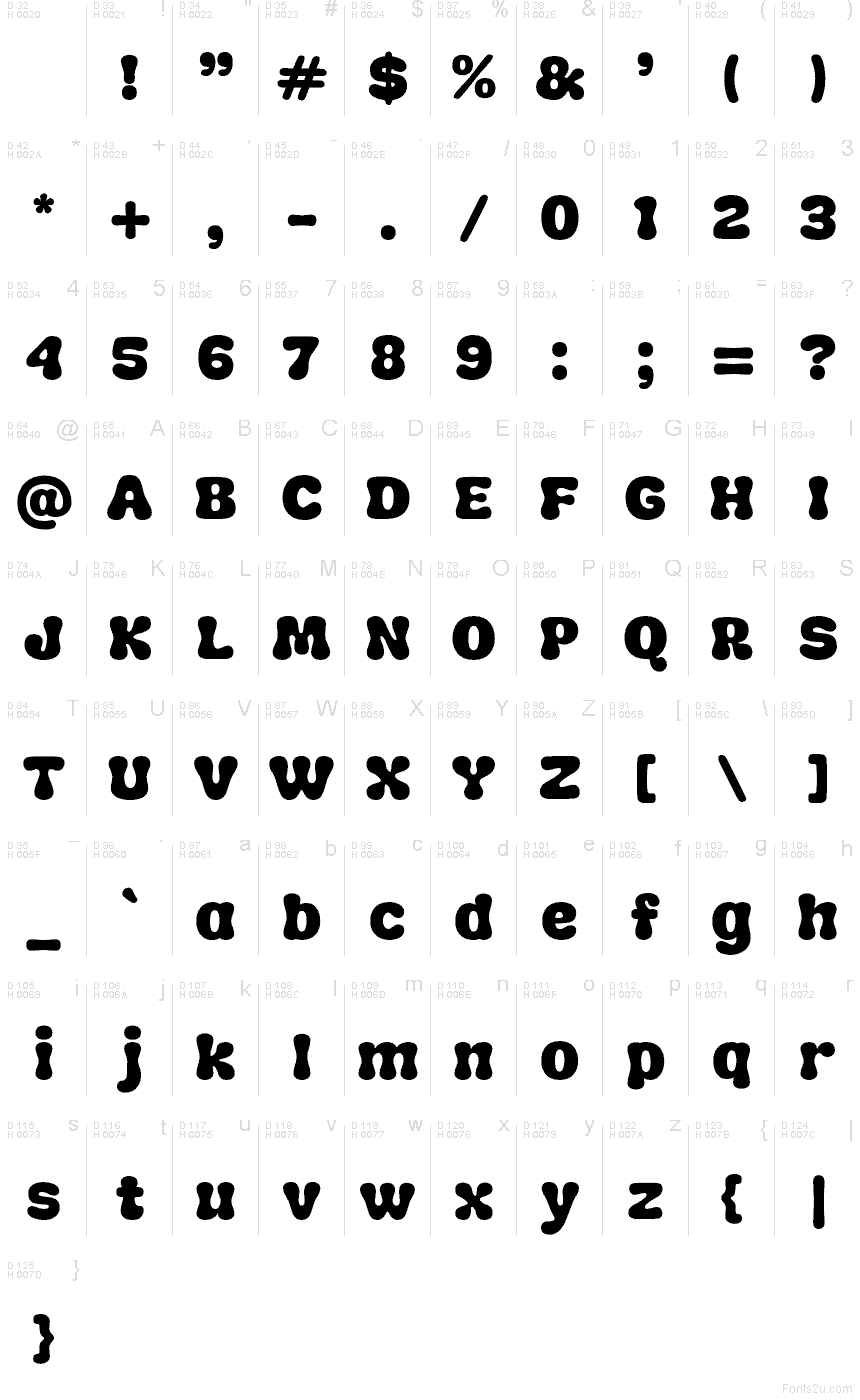
ChunkPlump-Regular
Chunk Plump od Viswell Studio je bezplatný groovy font typu display, definovaný měkkými, nafouklými siluetami, díky nimž každé písmeno působí vycpaně a lehce pružně. Široké zaoblené tvary a zúžené spoje dodávají písmu tekutý vzhled, který známe z plakátů 70. let, a který dalece přesahuje obyčejný „bublinový“ styl.
Tahle přehnaná měkkost vynikne na obalech alb, brandingu kaváren, designu samolepek, letácích na akce i na obalech sladkostí či dárkových předmětů. Krátké nadpisy, loga a grafika pro sociální sítě z něj těží nejvíce, protože nafouklé tvary vytvářejí přátelskou vizuální hmotu, která působí spíše jako tvarované litery než jako neutrální font.
Viswell Studio
Chunk Plump